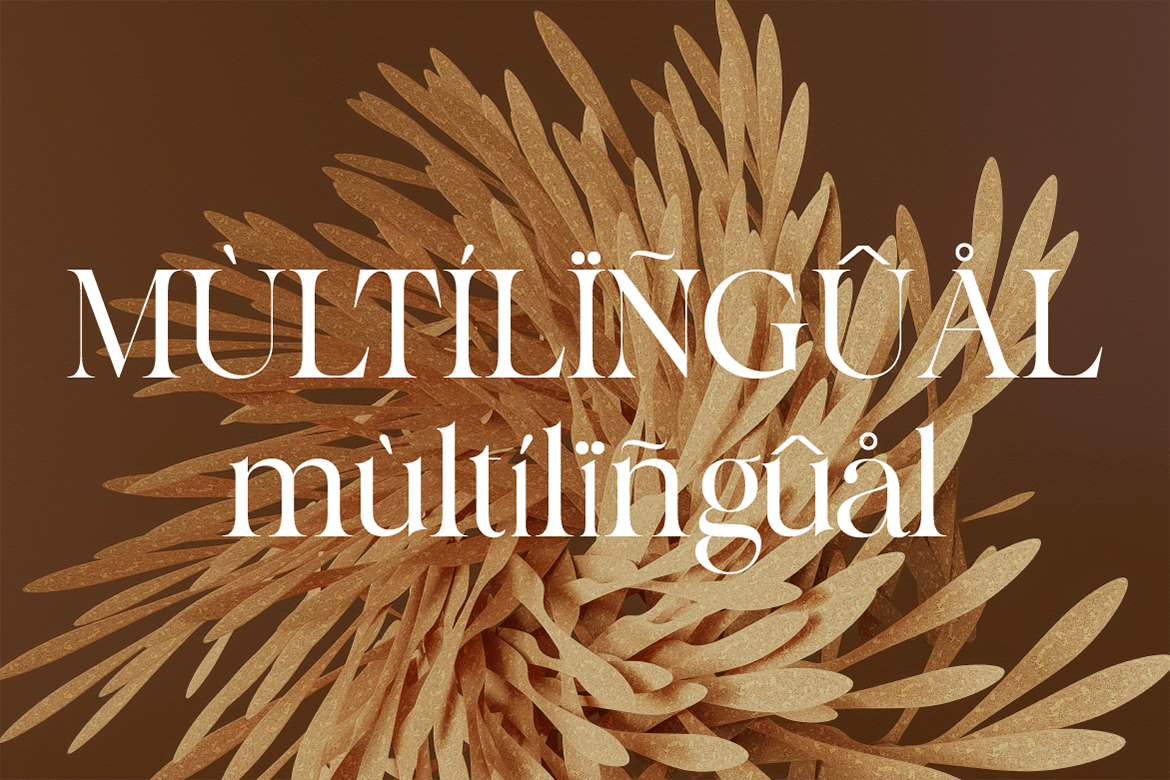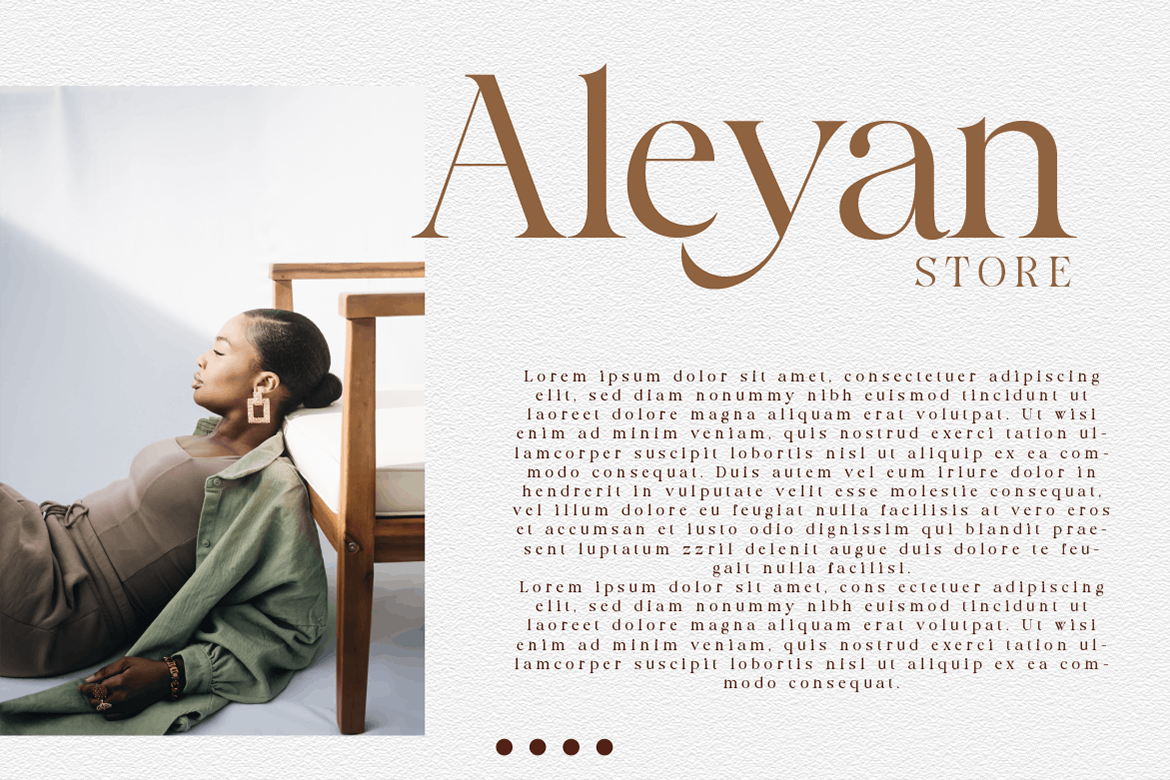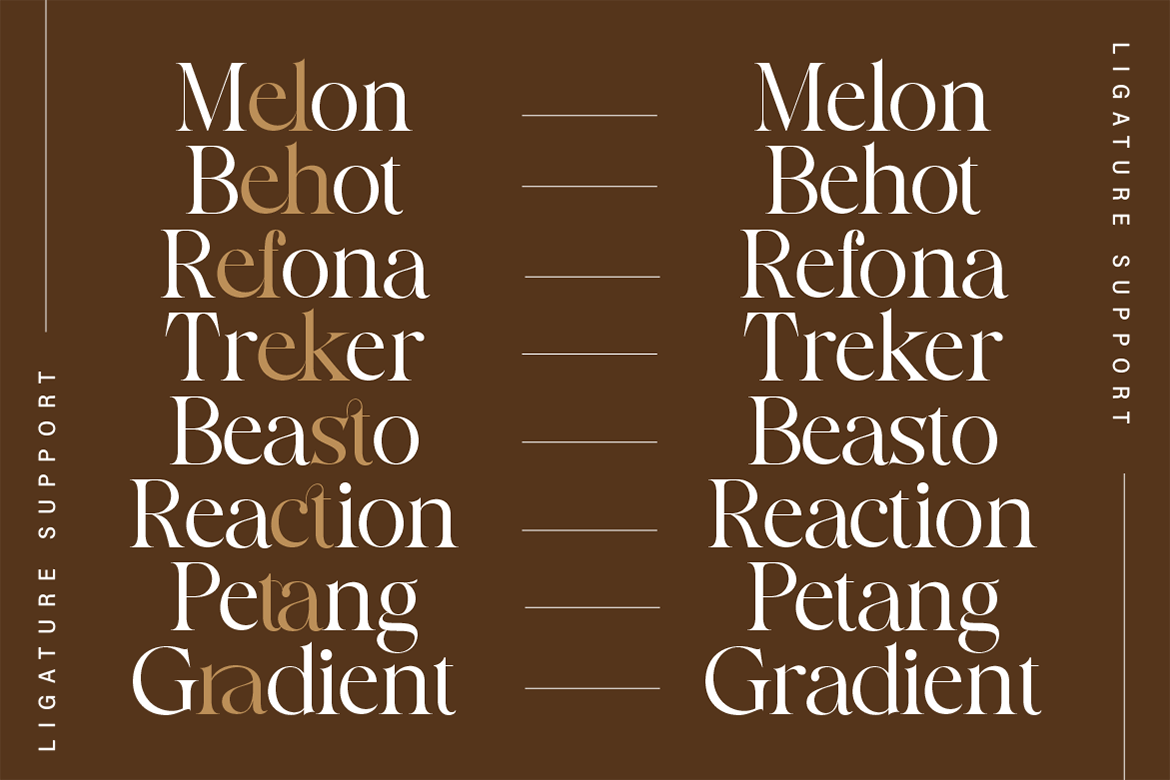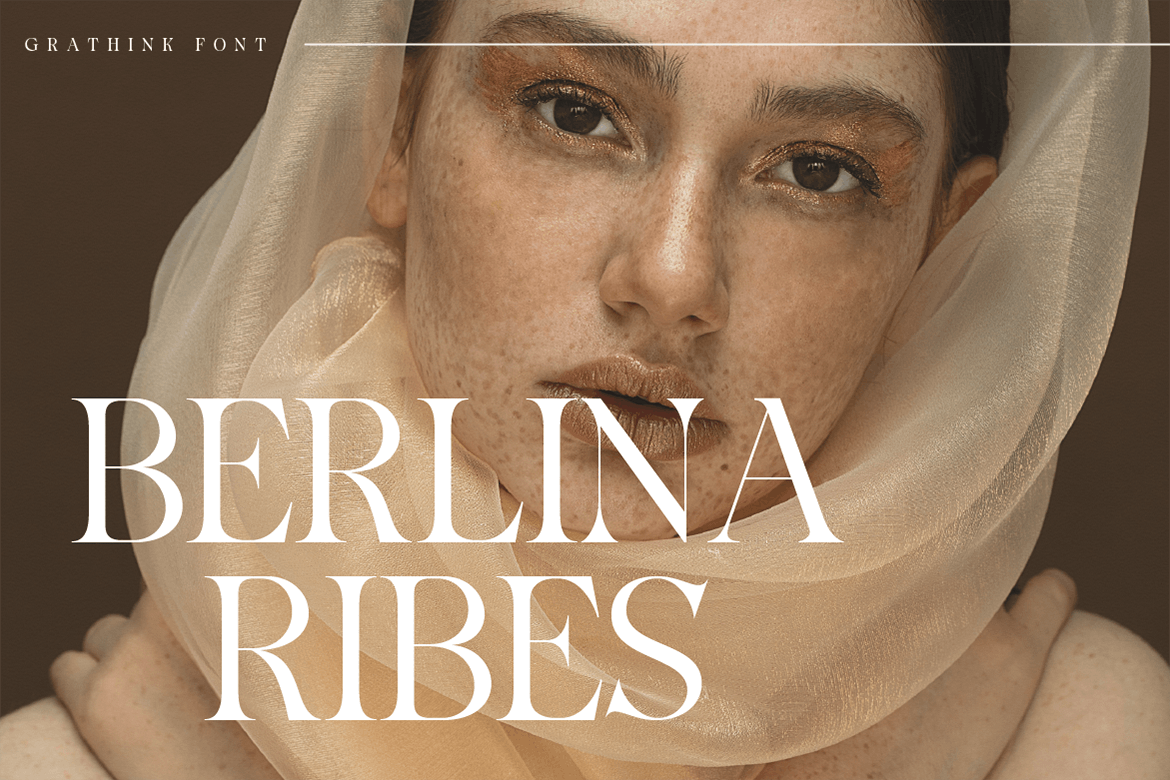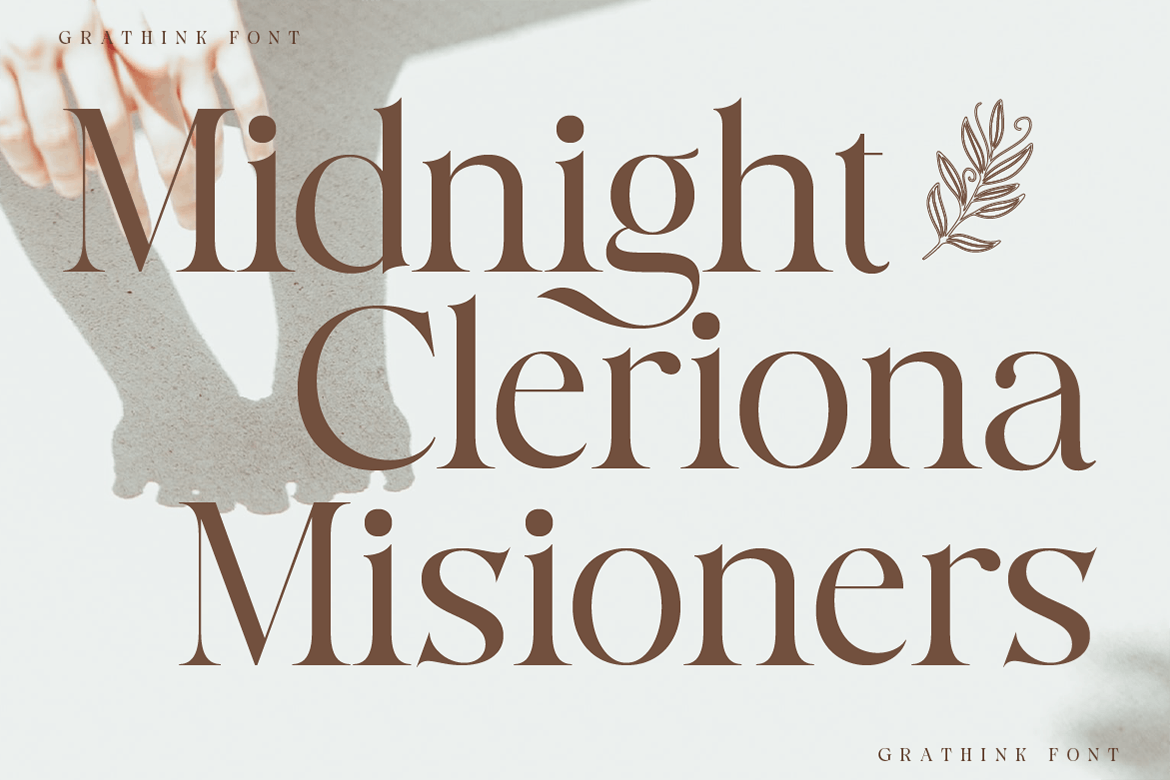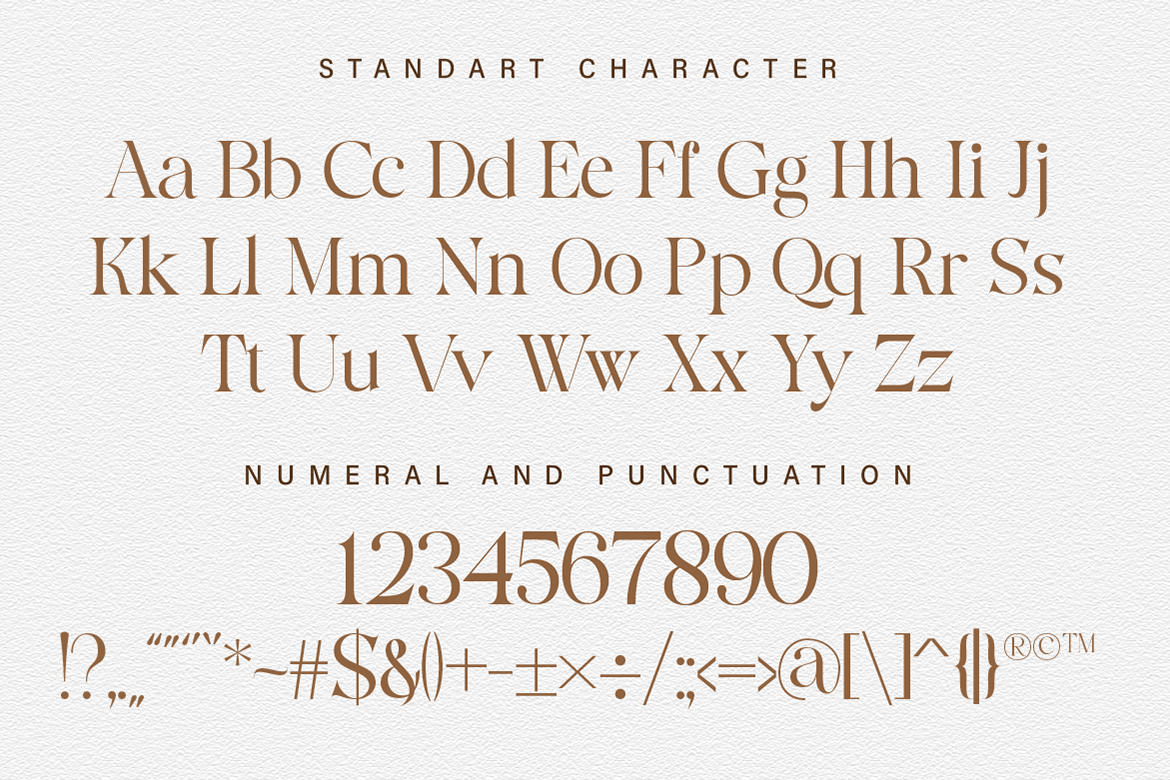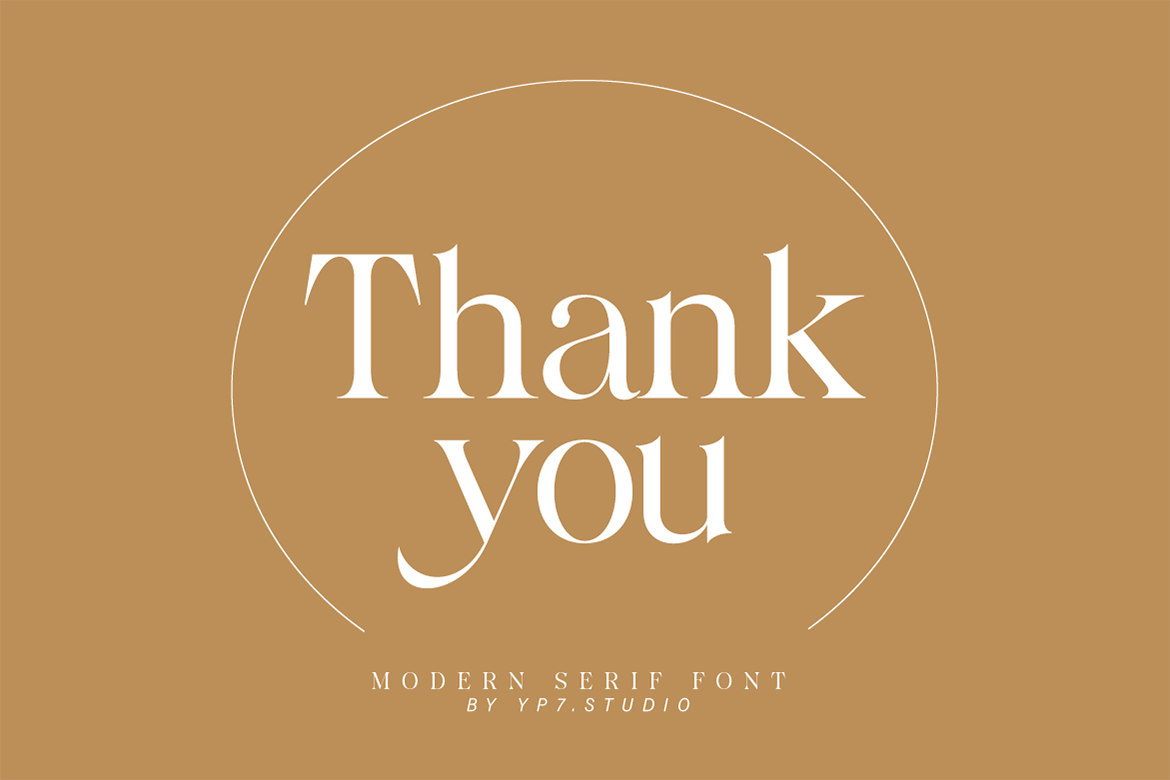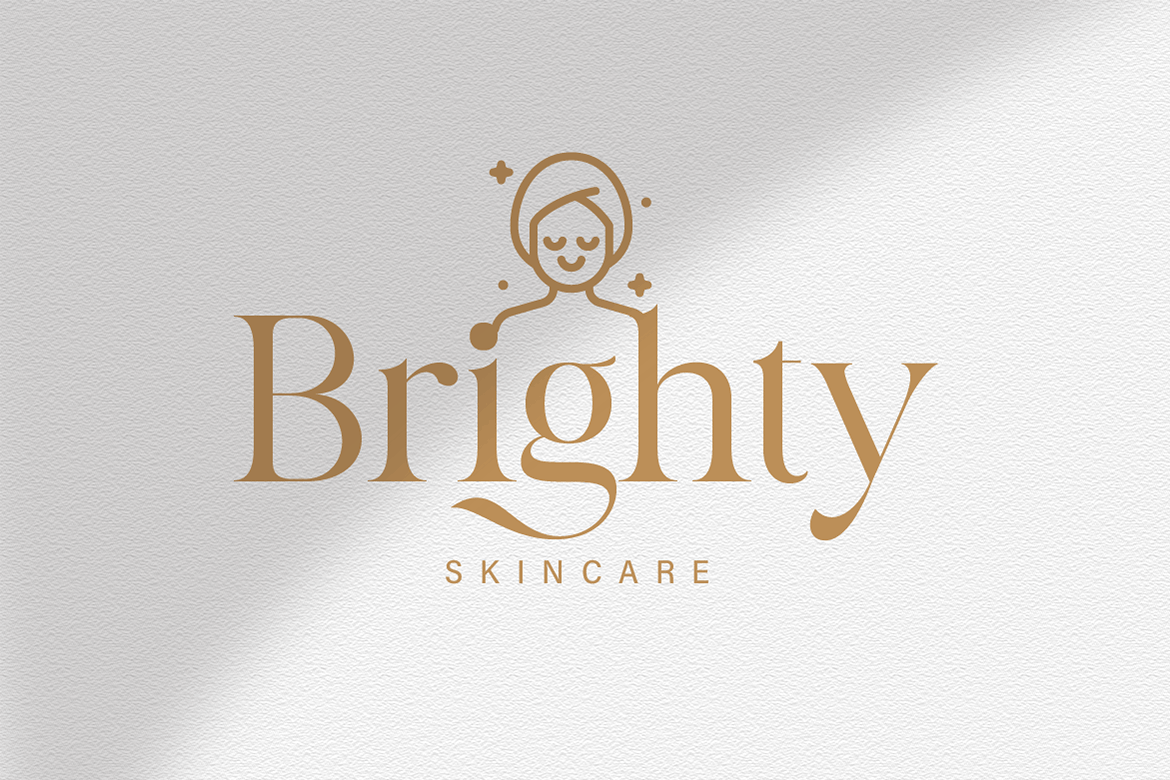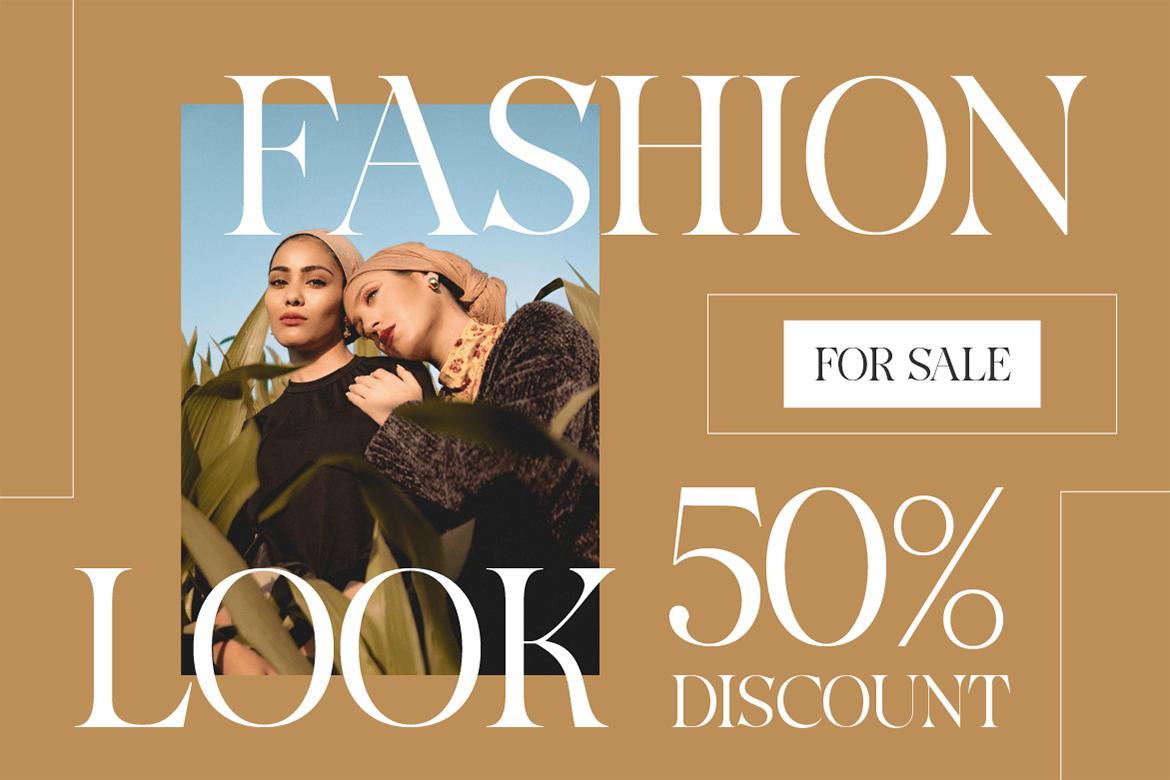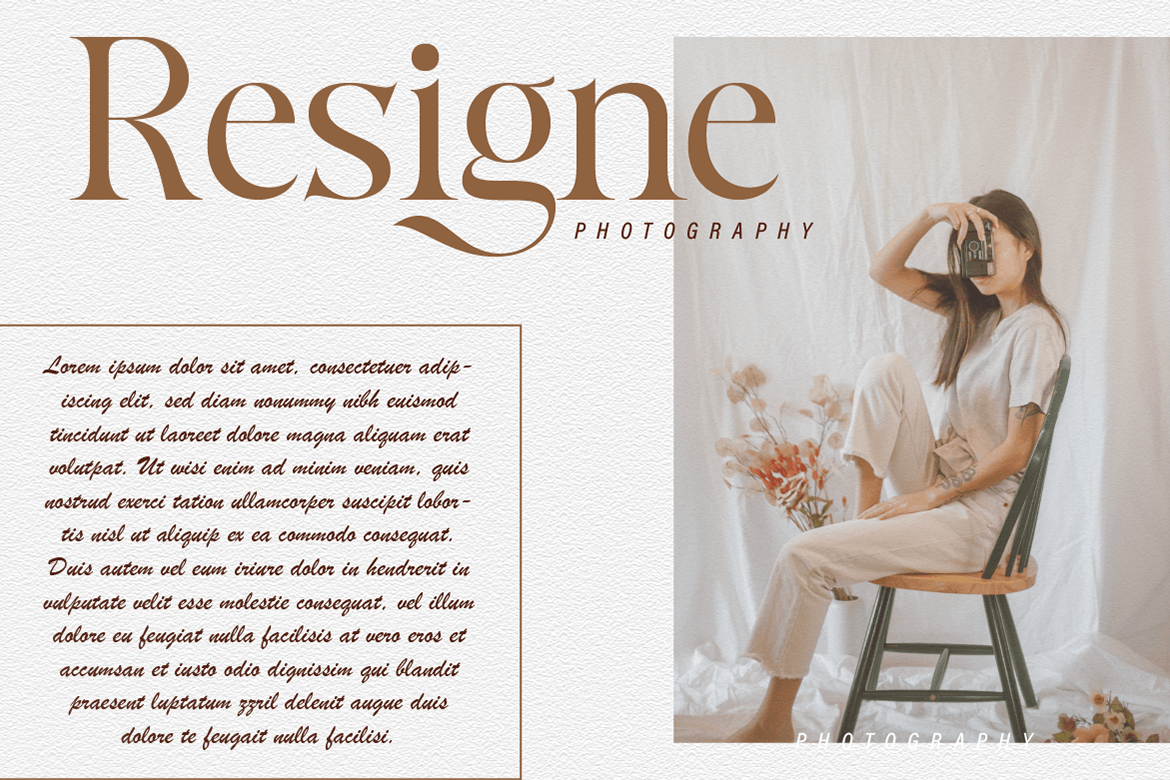
فونت مدرن سریف Grathink یک انتخاب فوقالعاده برای طراحان گرافیک است. این فونت با طراحی خاص و زیبا، جلوهای خاص به پروژههای شما میبخشد.
این فونت مناسب برای طراحیهای مختلف از جمله بروشورها، پوسترها و وبسایتها است. با دانلود این فایل، میتوانید به راحتی از آن در پروژههای خود استفاده کنید.